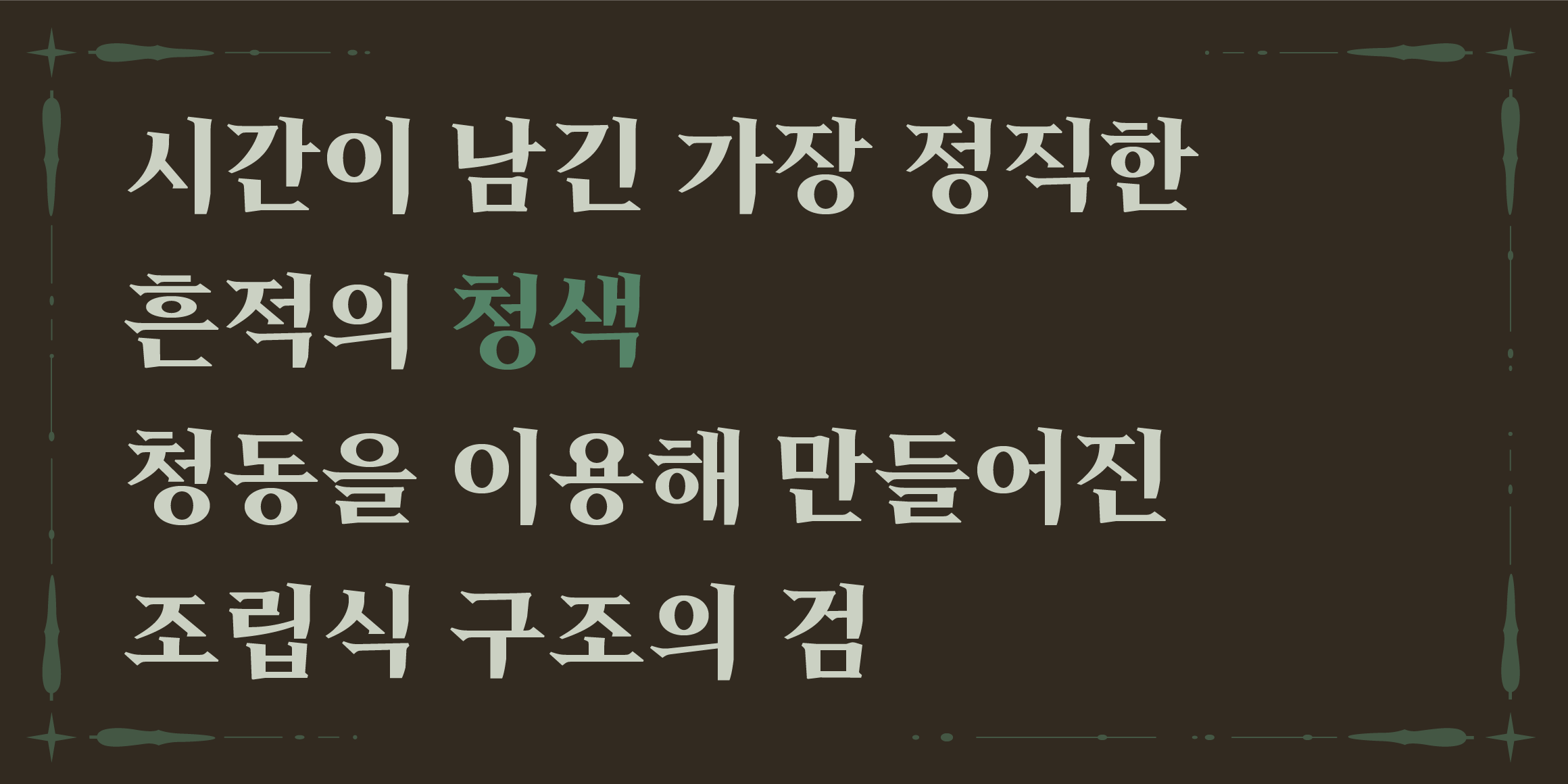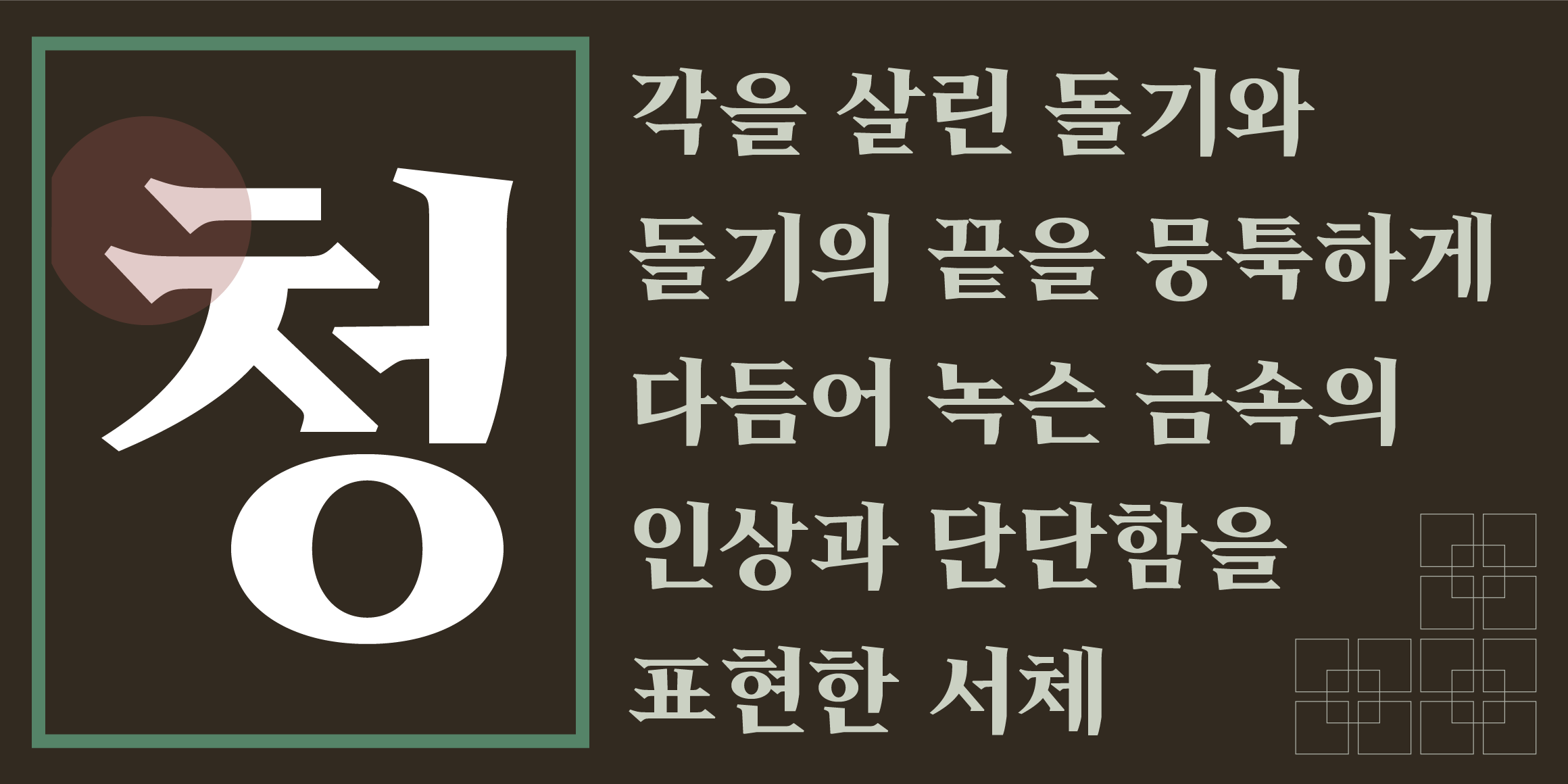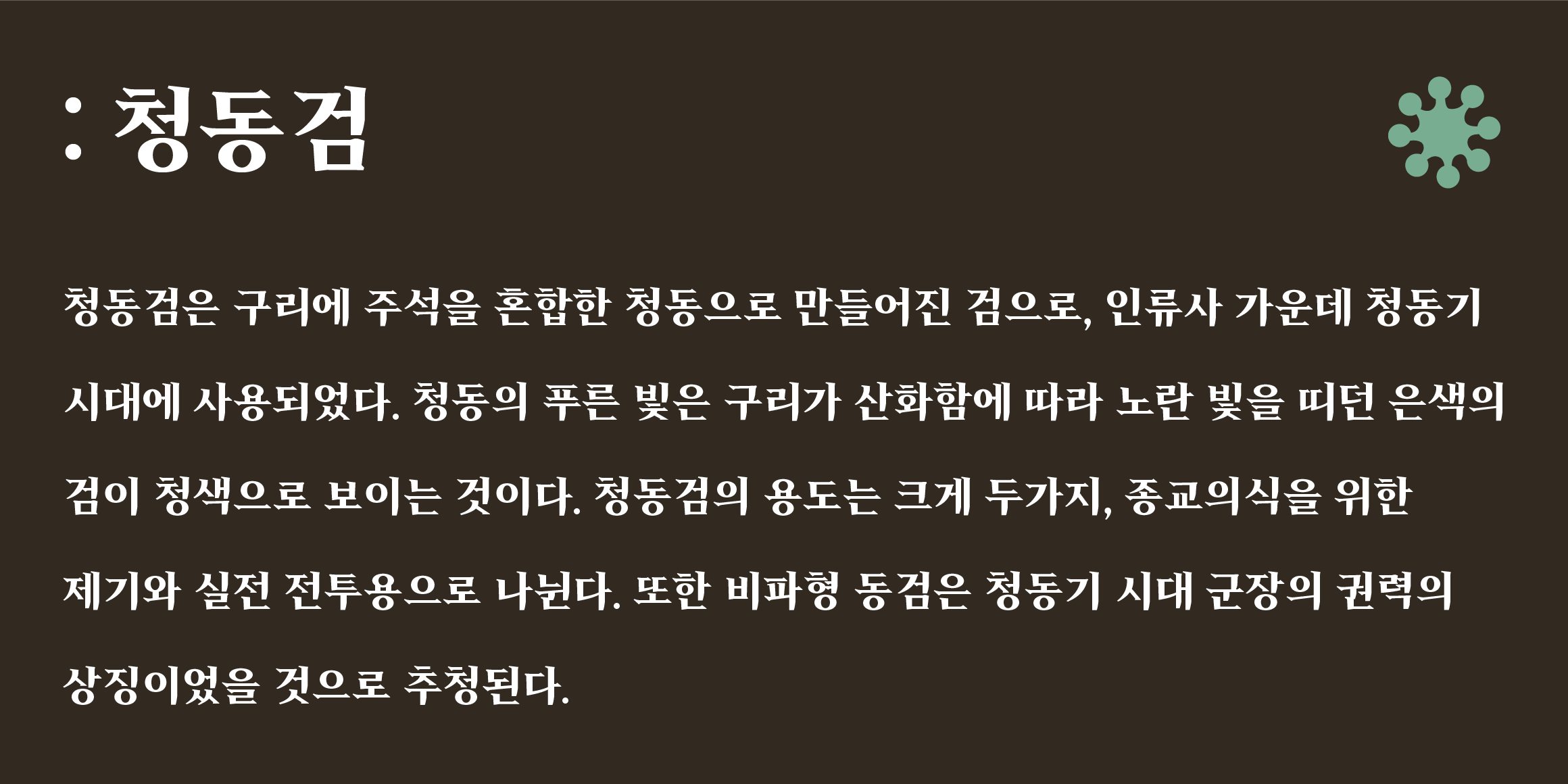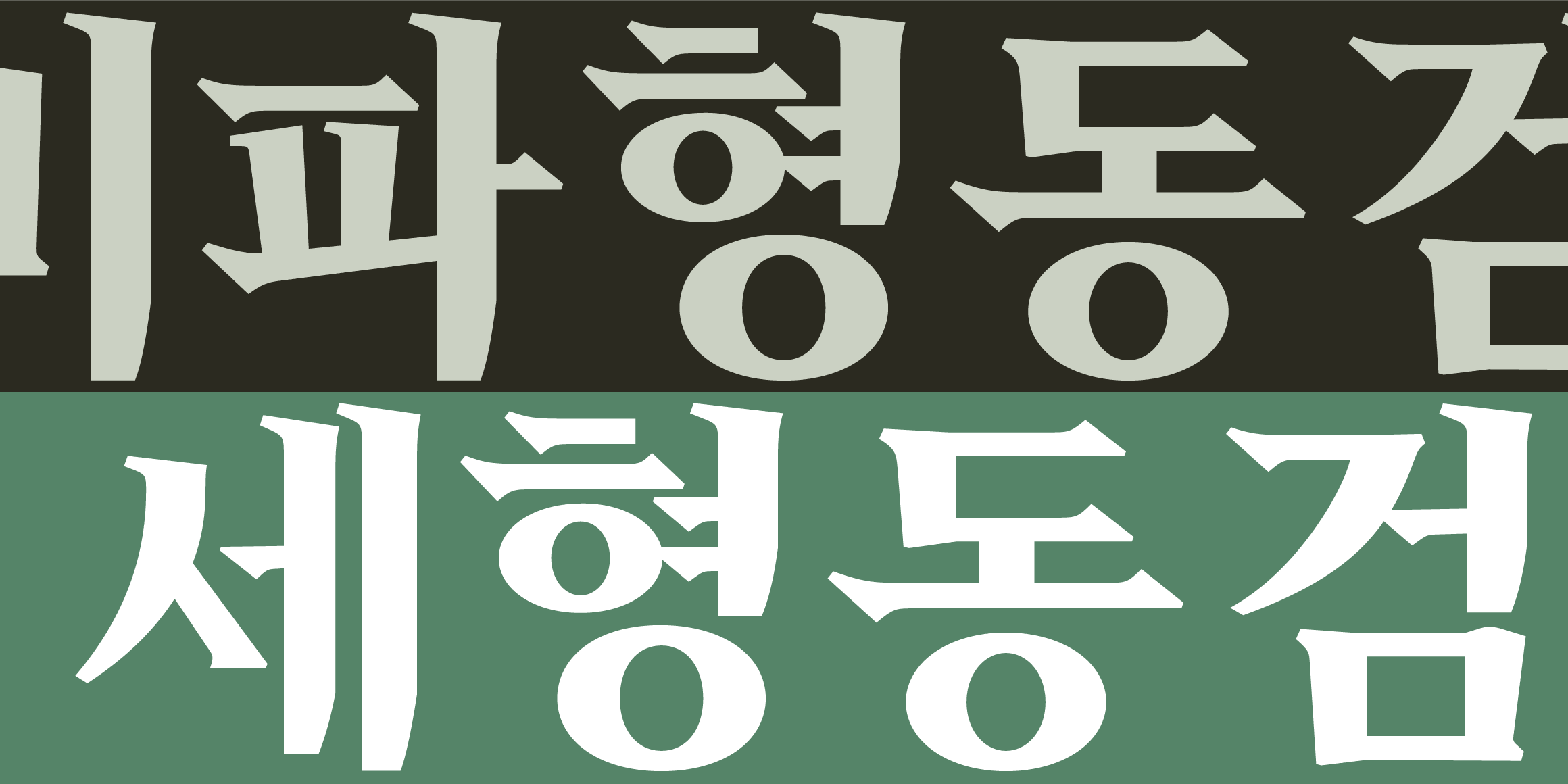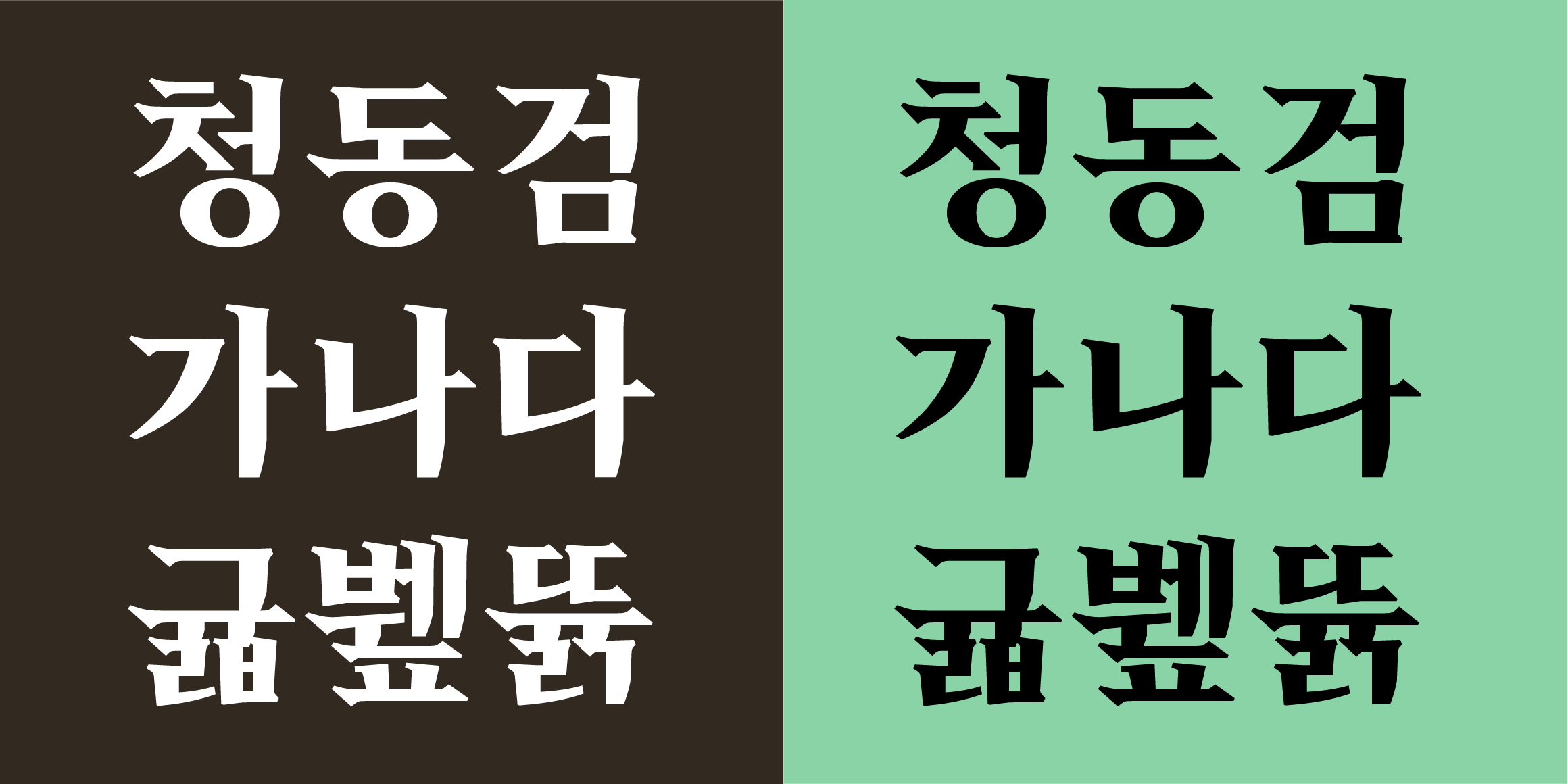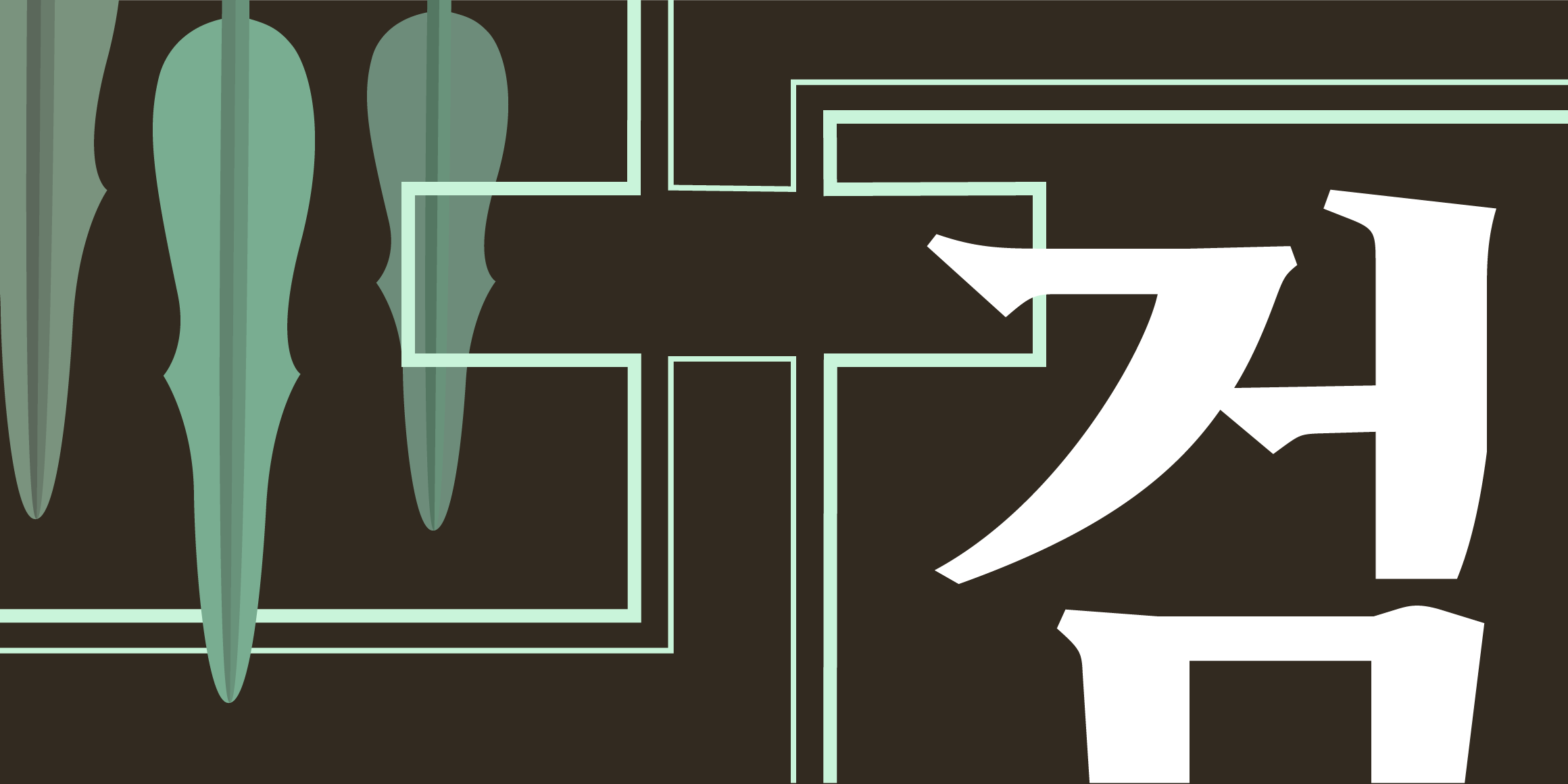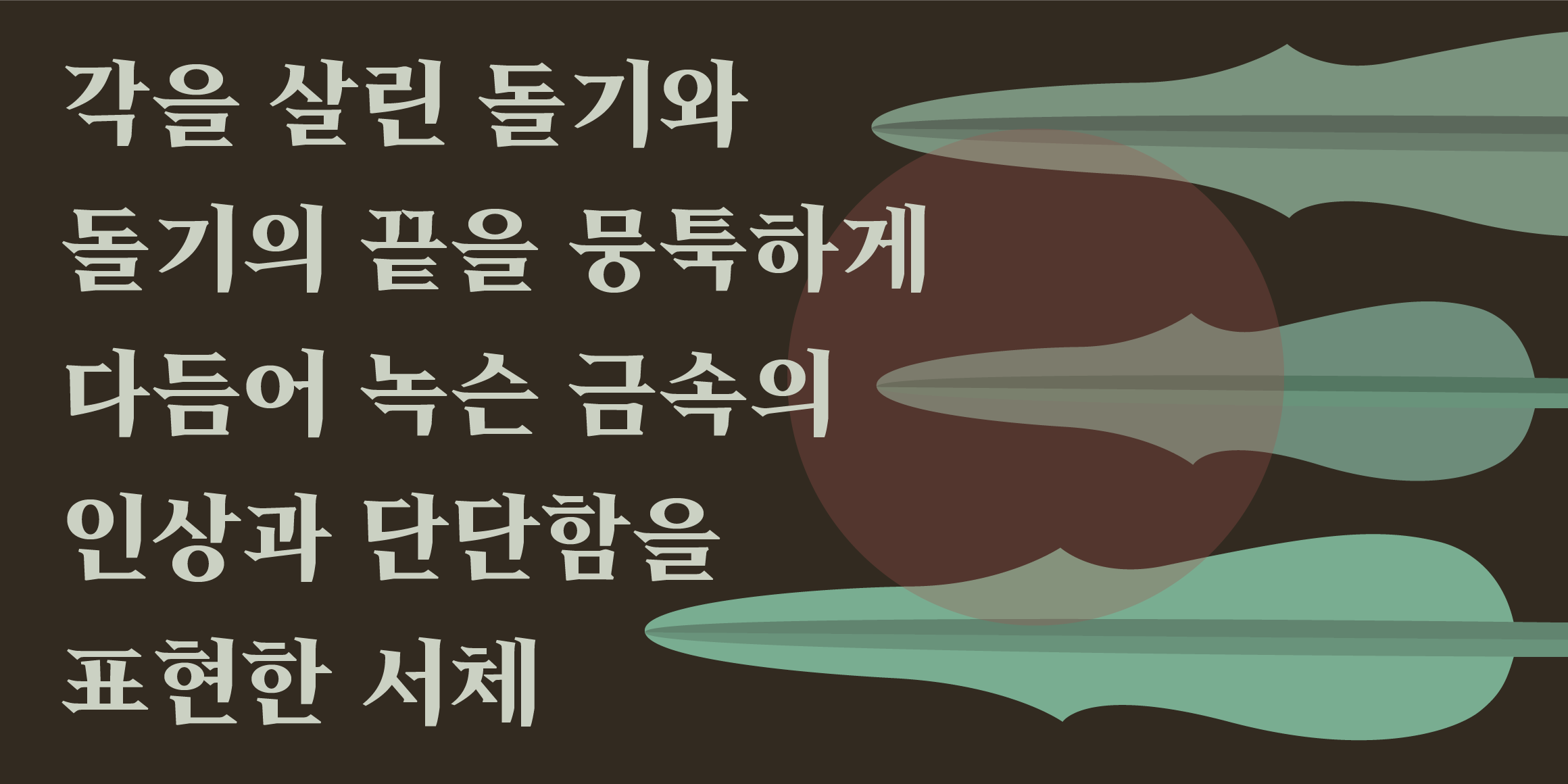
Tium 청동검체
분류 Display,부리
「Tium 청동검체」는 청동기 시대를 대표하는 유물인 청동검에서 영감을 받아 제작된 서체입니다. 비파형동검의 돌기와 오랜 세월을 거치며 자연스럽게 무뎌진 형태를 한글 세리프 디자인에 반영했으며, 세형동검의 날렵하고 단단한 실루엣을 바탕으로 직선적인 조형미를 강조했습니다. 이를 통해 유물이 간직한 시간의 흔적과 청동검 특유의 강인한 이미지를 현대적인 서체로 재해석했습니다.
• Tium 청동검체 / Tium BronzeDagger